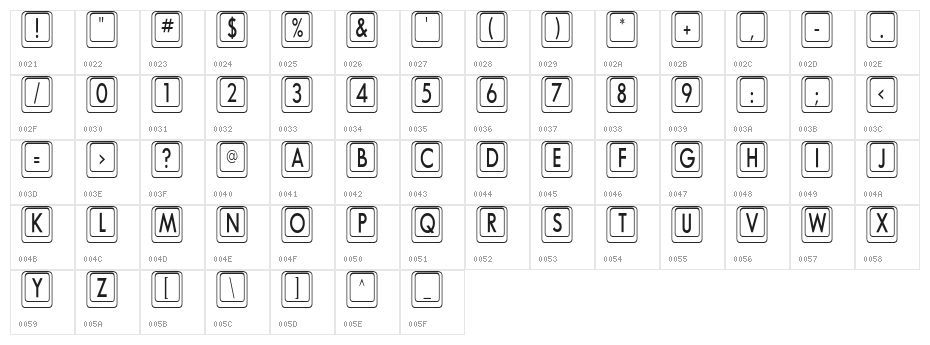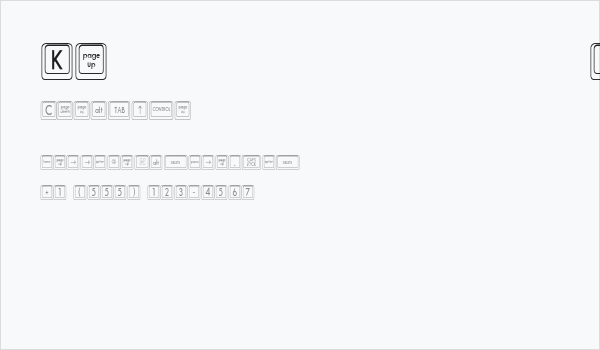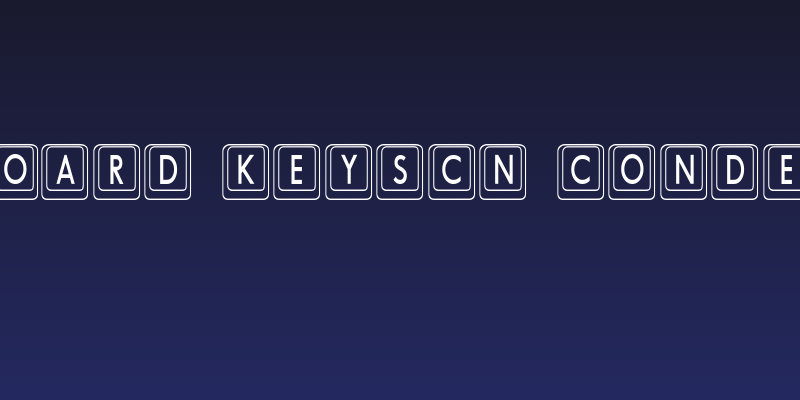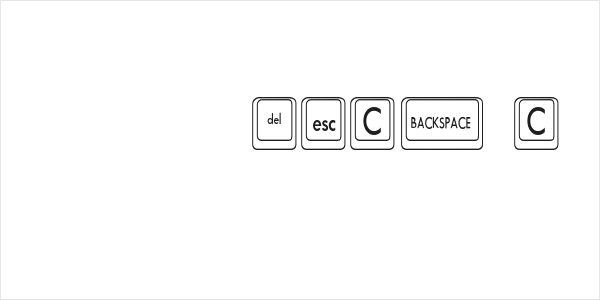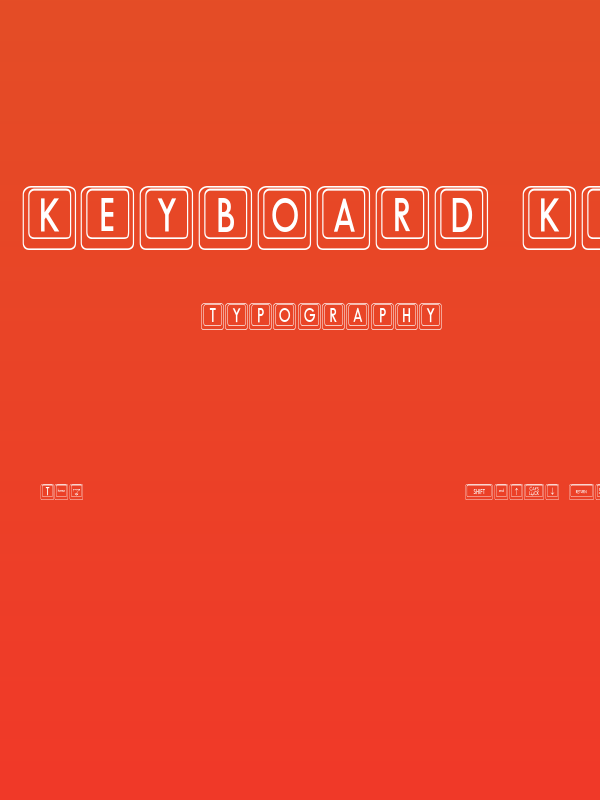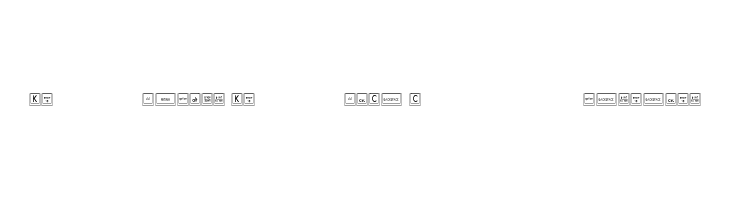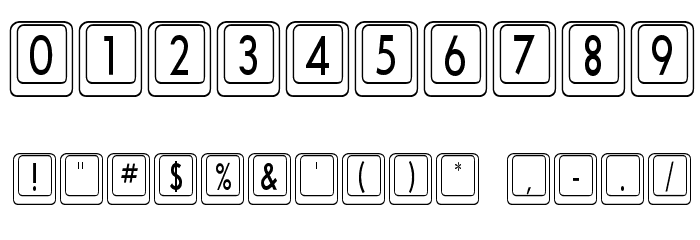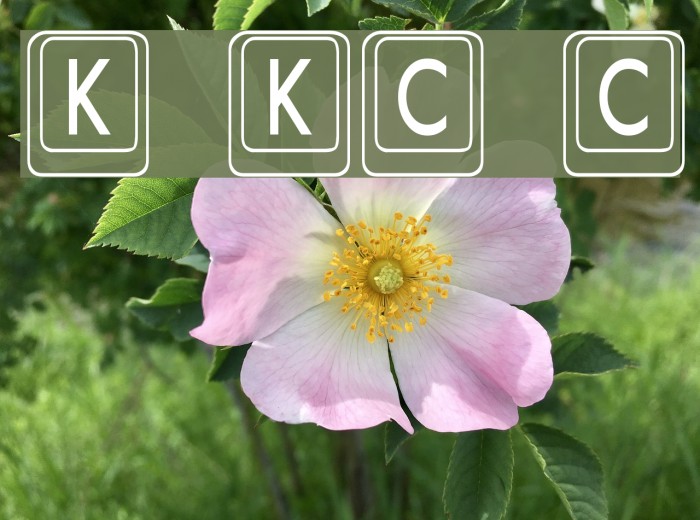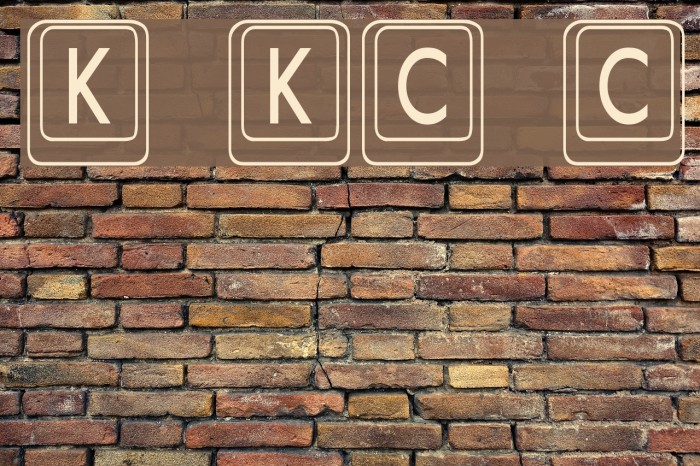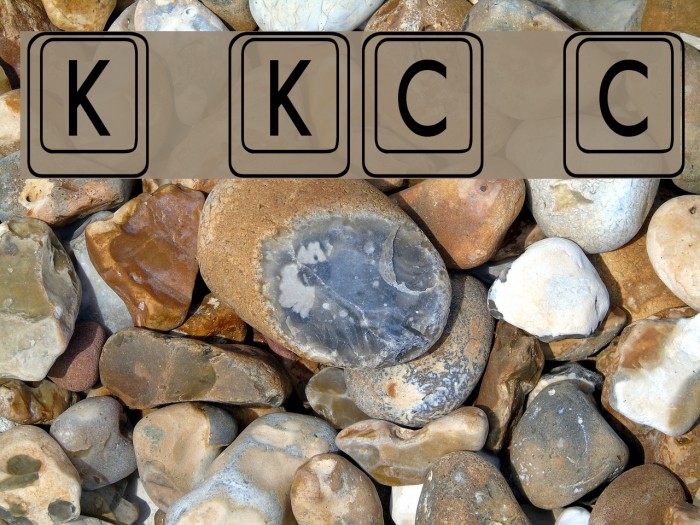
Keyboard KeysCn Condensed Font
| Stil general | Modern, Decorative |
| Caz de utilizare | Headlines, Logos, Digital Interfaces |
| Proiecte propuse | Ideal for tech-related designs, digital interfaces, educational materials, or any project requiring a modern, tech-inspired look. |